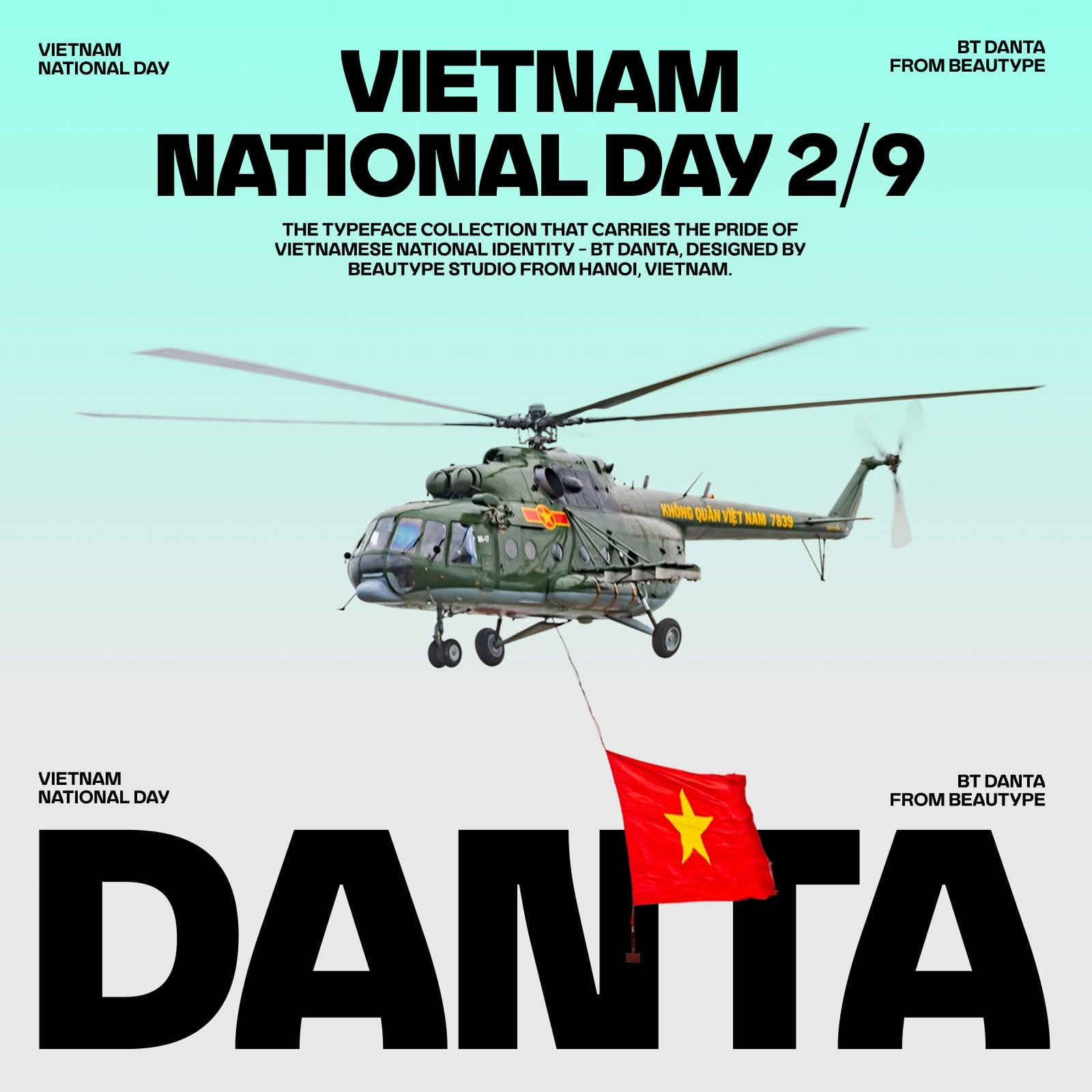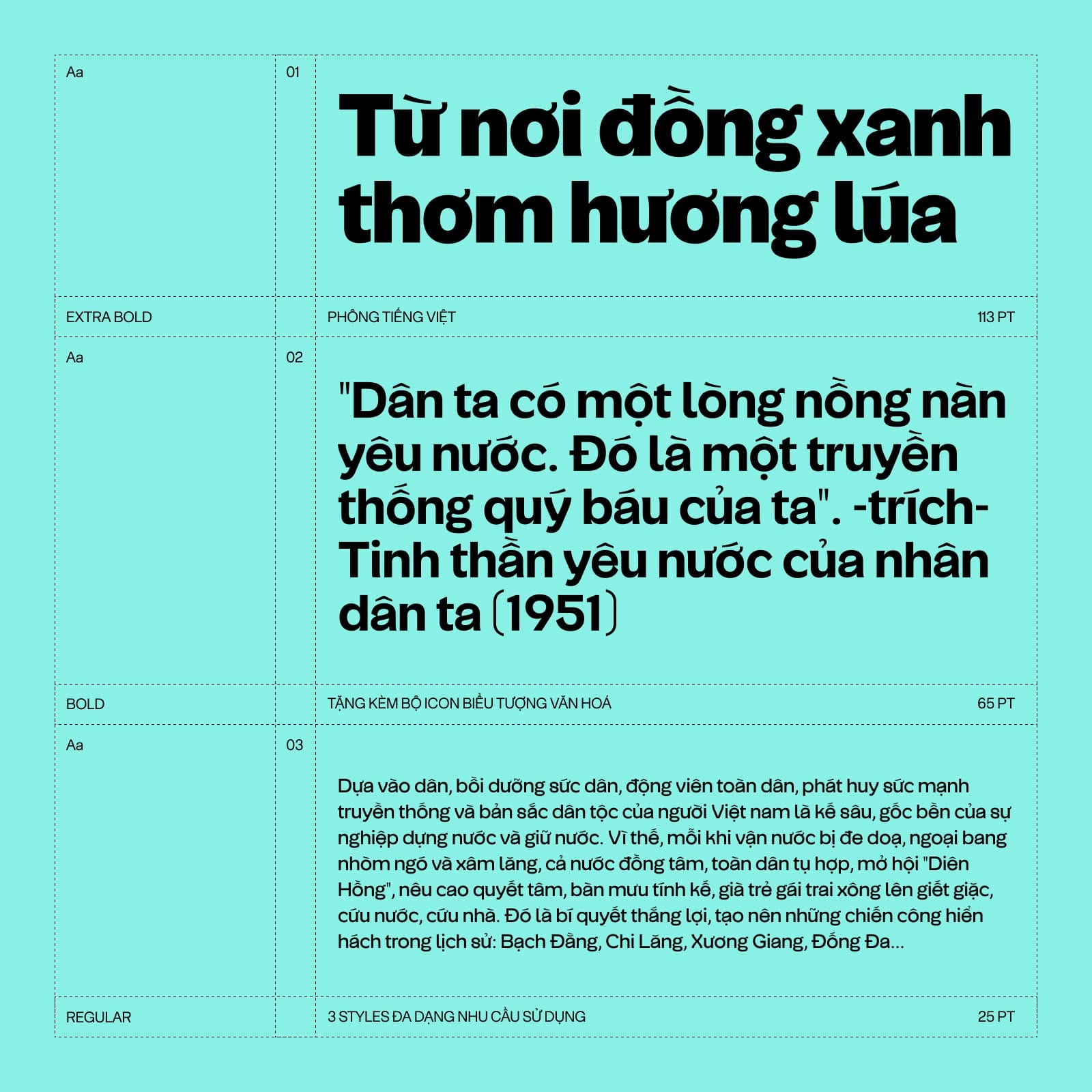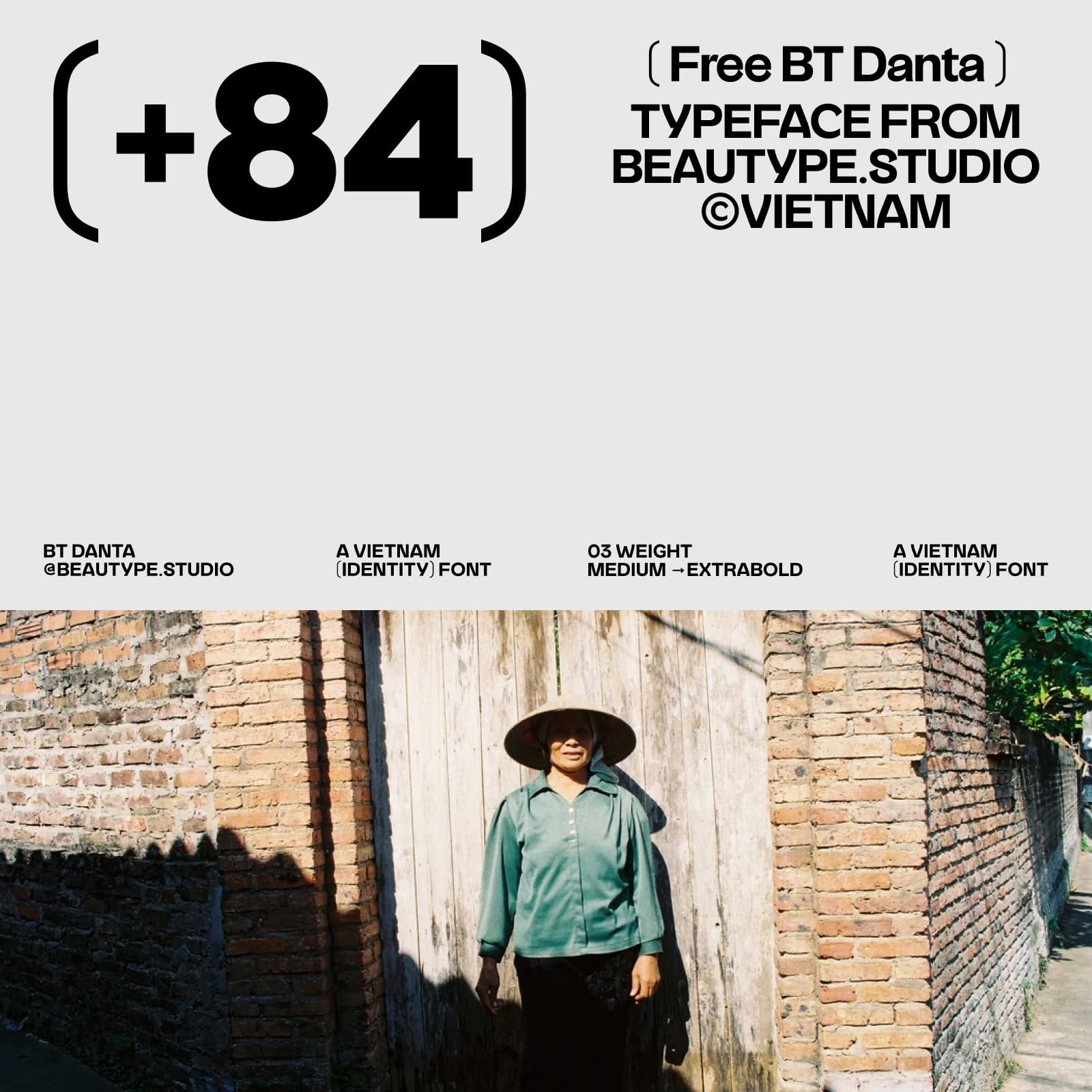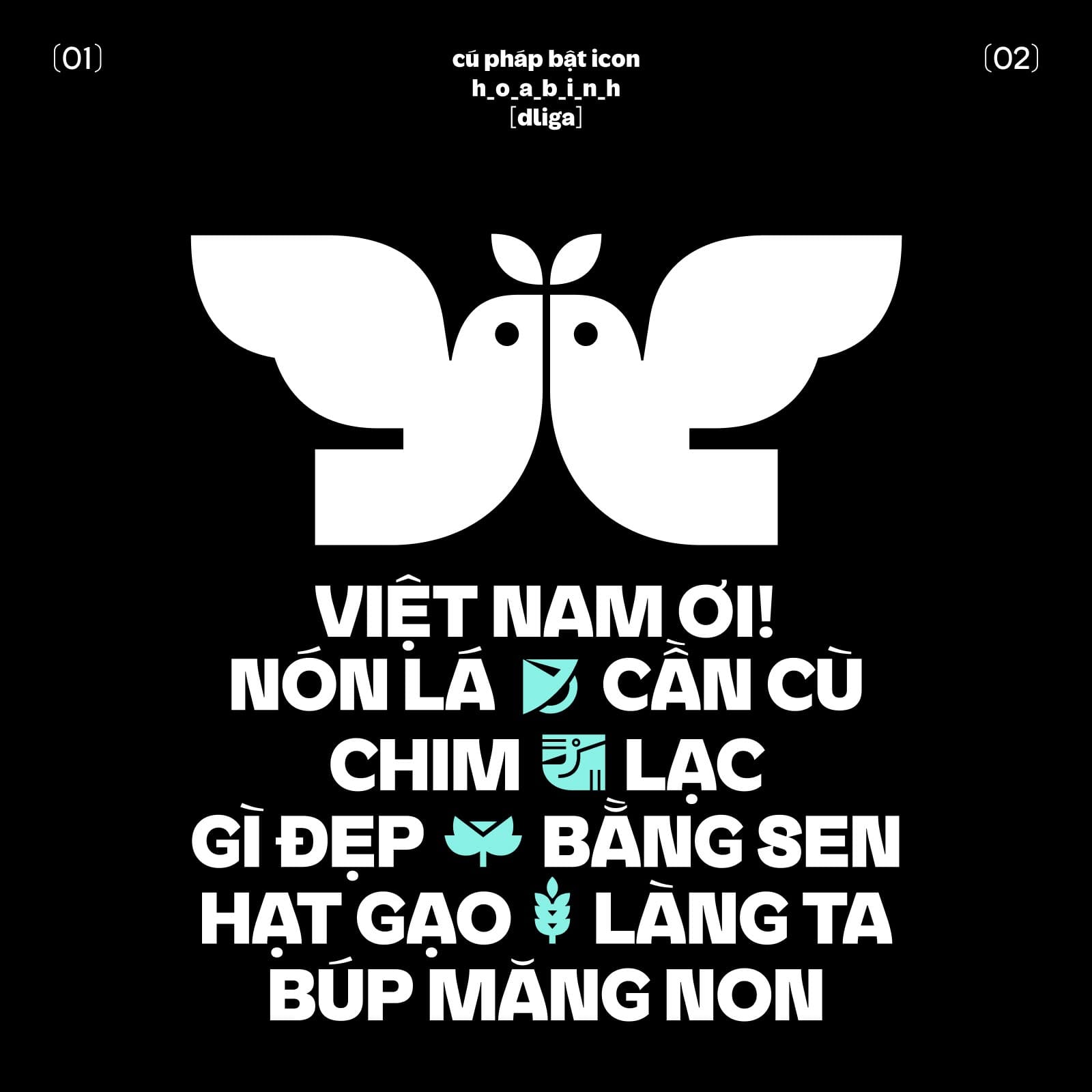
BT Danta Font là một trong những bộ font Việt miễn phí đáng chú ý dành cho những thiết kế cần cảm giác mạnh, gần gũi và có bản sắc. Không chỉ đơn thuần là một kiểu chữ để gõ tiêu đề, BT Danta mang trong mình một tinh thần rất riêng: tinh thần “Dân ta”, tinh thần cộng đồng và sự gắn kết của người Việt.
Trong thiết kế, có những font sinh ra để đọc lâu, có những font sinh ra để làm nền, nhưng cũng có những font được tạo ra để trở thành điểm nhấn chính của bố cục. BT Danta Font thuộc nhóm thứ ba. Đây là kiểu chữ phù hợp khi bạn cần một tiêu đề thật nổi bật, một poster có lực thị giác mạnh hoặc một ấn phẩm truyền thông cần tạo cảm xúc ngay từ cái nhìn đầu tiên.
BT Danta Font mang tinh thần Việt theo cách rất hiện đại
Điểm hay của BT Danta không nằm ở việc cố gắng trang trí quá nhiều, mà nằm ở cách font tạo cảm giác chắc chắn, đồng bộ và có khí chất. Những đường nét dày dặn, cấu trúc chữ rõ ràng và cách xử lý dấu tiếng Việt giúp bộ font này vừa dễ nhận ra, vừa giữ được sự gần gũi cần thiết trong các thiết kế dành cho người Việt.
Khi đặt BT Danta trong các bố cục lớn như poster, banner, thumbnail hoặc key visual, font cho cảm giác rất “có tiếng nói”. Chữ không bị yếu, không bị chìm và cũng không cần quá nhiều hiệu ứng phụ để trở nên nổi bật. Chỉ cần chọn đúng màu sắc, khoảng cách chữ và bố cục, BT Danta đã đủ sức trở thành trung tâm của thiết kế.
Phù hợp với poster, sự kiện và truyền thông cộng đồng
Nếu bạn thường làm các thiết kế liên quan đến sự kiện, lễ hội, hoạt động cộng đồng, chương trình văn hóa hoặc chiến dịch truyền thông mang tinh thần Việt, BT Danta Font là một lựa chọn rất đáng thử. Font có chất display rõ ràng, hợp với những cụm chữ ngắn, khẩu hiệu, headline hoặc các dòng thông điệp cần truyền tải nhanh.
BT Danta cũng phù hợp với các thiết kế social media cần sự nổi bật. Với những bài đăng dạng thông báo sự kiện, poster cổ động, ảnh bìa chương trình, thumbnail video hoặc banner quảng bá, bộ font này có thể giúp phần chữ trở nên có trọng lượng hơn mà vẫn giữ được cảm giác thân thuộc.
Font có dấu tiếng Việt sẵn, dùng tiện cho thiết kế Việt
Một ưu điểm quan trọng của BT Danta là font hỗ trợ tiếng Việt sẵn. Điều này rất cần thiết với các designer thường xuyên làm việc với nội dung tiếng Việt, vì dấu chữ ảnh hưởng trực tiếp đến chất lượng thị giác của thiết kế. Một font đẹp nhưng dấu lệch, dấu quá cao, quá thấp hoặc không đồng bộ sẽ rất dễ làm hỏng tổng thể.
Khi nào nên dùng BT Danta Font?
BT Danta Font phù hợp nhất khi dùng ở kích thước lớn. Bạn có thể dùng font cho tiêu đề poster, tên sự kiện, slogan, banner, bìa bài viết, ảnh social media, thiết kế văn hóa, dự án cộng đồng hoặc các ấn phẩm cần cảm giác mạnh mẽ và rõ bản sắc.
Tuy nhiên, vì đây là font display có cá tính thị giác mạnh, BT Danta không phải lựa chọn tối ưu cho đoạn văn bản dài. Nếu cần trình bày nội dung nhiều chữ, bạn nên kết hợp BT Danta với một font sans-serif dễ đọc hơn như Be Vietnam Pro, Inter hoặc một font body trung tính. Cách kết hợp này giúp thiết kế vừa có điểm nhấn, vừa giữ được sự dễ đọc.
Nếu bạn đang tìm một font tiếng Việt miễn phí có dấu sẵn, mang tinh thần Việt và phù hợp cho các thiết kế tiêu đề, BT Danta Font là một lựa chọn rất nên lưu lại. Bộ font này đặc biệt hợp với những dự án cần sự mạnh mẽ, gần gũi, cộng đồng và có cảm xúc văn hóa rõ ràng.
BT Danta không chỉ là một font để làm đẹp chữ, mà còn là một chất liệu thị giác giúp thông điệp trở nên có sức nặng hơn. Với các thiết kế poster, sự kiện, branding, social media hoặc những ấn phẩm dành cho cộng đồng Việt, đây là bộ font miễn phí rất đáng để thử trong thư viện font của bạn.